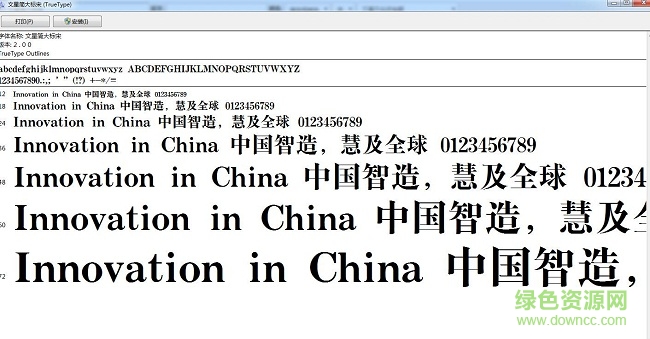
文星簡大標(biāo)宋字體是一款實用性強的免費標(biāo)宋字體,粗細(xì)對比比小標(biāo)宋字體更加明顯,規(guī)范嚴(yán)謹(jǐn),端正大氣,適合用作做書面文件的大標(biāo)題,有需要者歡迎在綠色資源網(wǎng)下載!
宋體字名為宋體,其實誕生在明朝,而其根本原因是明清兩代文人仰慕宋朝文化、追捧宋刻本所致。到了清代,宋體字進(jìn)一步發(fā)展,康熙中期以后逐漸形成清代的風(fēng)格。最明顯的特征在于此時的宋體字字形比明末清初更方正,更接近于后來我們熟悉的印刷體。到乾隆時期,宋體字已大體定型,其橫畫收筆的三角、豎畫起筆的三角等,與現(xiàn)代宋體字基本相同。